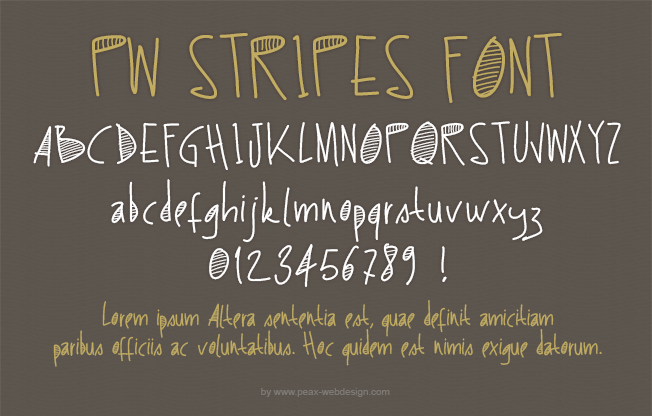
PW Stripes, police manuscrite au format .ttf.
PW Stripes est une police irrégulière, à l'aspect manuscrit et présentant à l'intérieur de certaines lettres des rayures qui font sa personnalité. Elle est très décorative en utilisation pour des titres, mais PW Stripes est également lisible dans des tailles plus petites. Son usage sur fond foncé ou coloré est particulièrement attrayant.